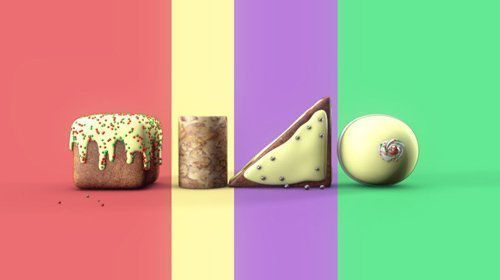
¿Qué tienen en común las fiestas navideñas, la celebración de fin de año y la llegada de los Reyes Magos? «La comida», asegura Plenty.tv. Por eso la compañía tomó chocolates, caramelos, galletas y azúcar en todas sus modalidades para las cortinillas de fin de año del canal estadounidense MTV Tr3s. La empresa argentina acaba de publicar las tres piezas y fotogramas de cada una de ellas.
«Nos lanzamos a la búsqueda de los sabrosos ingredientes para cada una de las fiestas y los utilizamos para generar unas divertidas composiciones tipográficas con un único mensaje: el logo de MTV Tr3s», explican en su web.
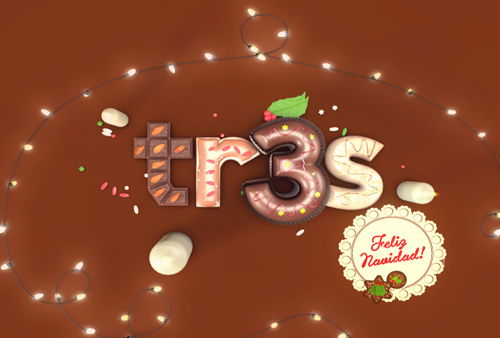
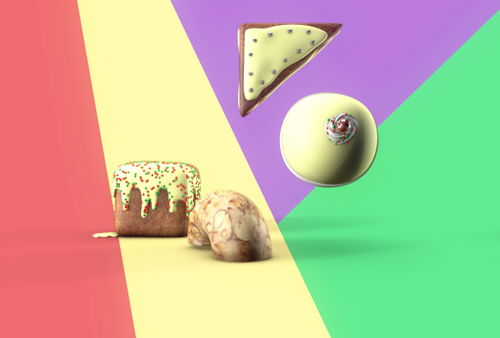
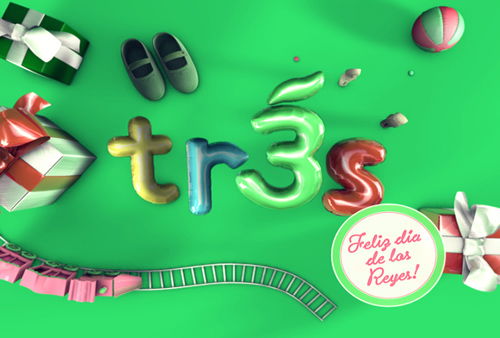
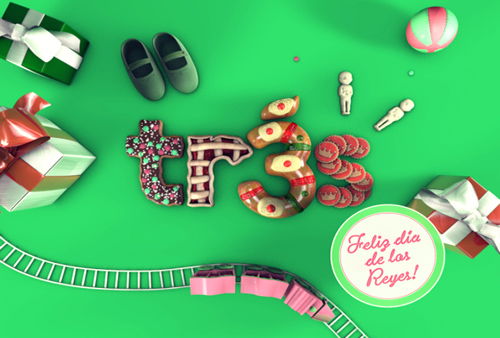
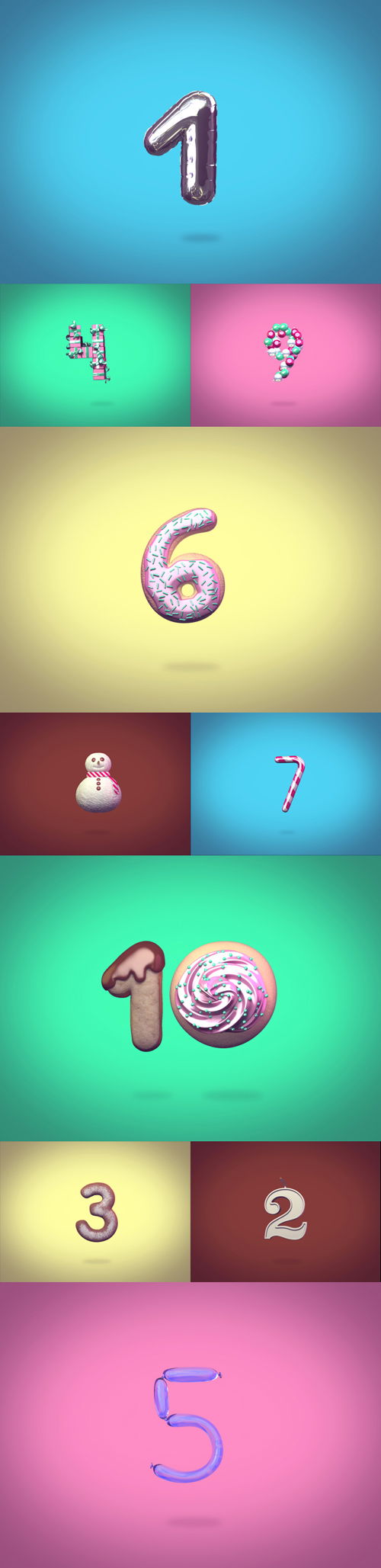
Tipografías de chocolate y galletas